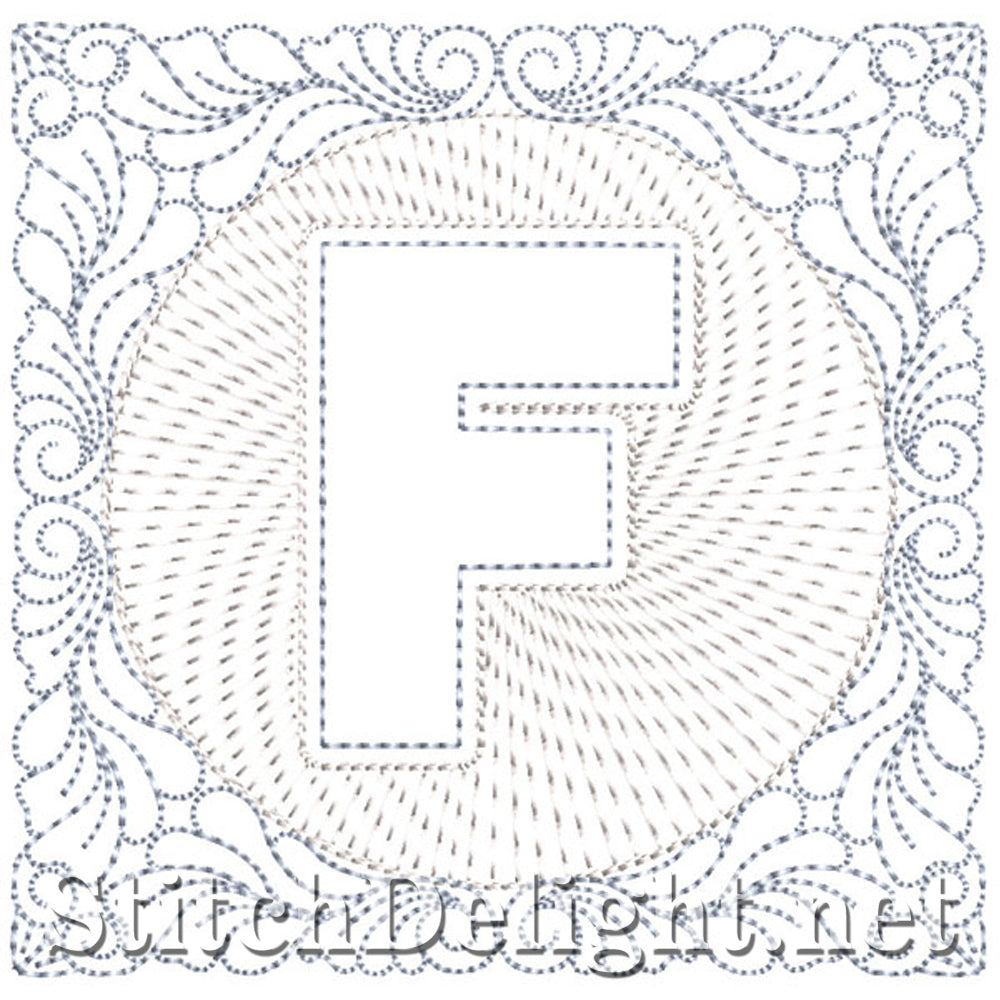
SDS1185 Quilters Bloc Police F
Cette belle police est magnifique lorsqu'elle est cousue sur un sandwich de coupe, de molleton et de tissu - le tissu extensible donne un gonflant élevé époustouflant - épelez un nom ou faites une courtepointe alphabet - Celles-ci sont réalisées dans le cerceau 4x4 (vous pouvez agrandir à volonté) La taille du bloc est de 3,74x3,74" et le nombre de points est de plus ou moins 6600 points